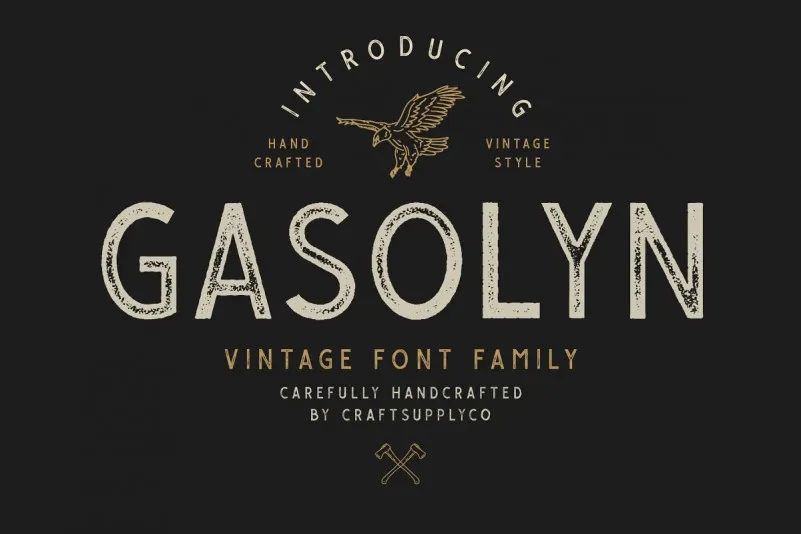
Gasolyn Font – Fonte Grátis
Gasolyn Font
A Gasolyn Font é uma fonte Display que apresenta um toque elegante clássico com textura de ferrugem, ideal para criar projetos digitais que pareçam autografados a mão. Esta fonte tem um charme singular e uma personalidade única que dá vida aos seus trabalhos de design impresso ou digital. Seja em cartazes, logos, letras do site ou até mesmo nos banners de redes sociais – ela enriquece qualquer projeto com sua textura rústica e estilo único. Com apenas algumas adições de criatividade e elementos gráficos adicionados no Extra, a Gasolyn Font pode transformar seu design em algo extraordinariamente vivo e incrivelmente profissional ao mesmo tempo. Sempre lembrando que esta é uma fonte para ser usada com moderação e critério, já que sua textura rústica poderia não se adequar bem para todos os contextos de design. Mas certamente ela adicionará um toque único a qualquer projeto que você decida usar!